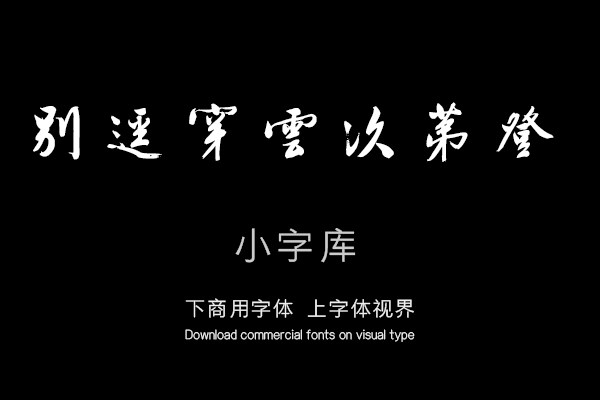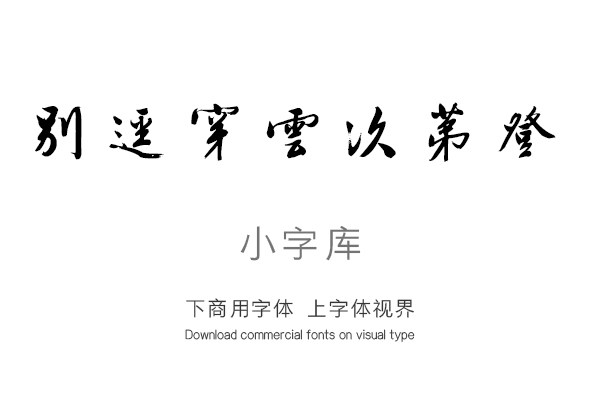
《汉标文徵明漫录旧作》是一款根据明代文徵明《漫录旧作》,经过再次调整制作的小字库,该小字库共收录了该真迹作品中约90个字体。单字授权
入门连岭翠崚嶒,别迳穿云次第登。碧瓦参差莲宇动,苍藤阴翳紫厓崩。眼中历历悲陈迹,方外悠悠愧老僧。十载同游半零落,长明惟有佛前灯。嘉靖癸丑春,归自虎丘,漫录旧作,时年八十有四。徵明。